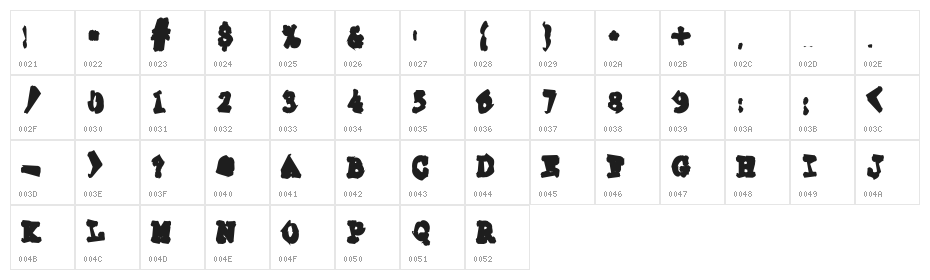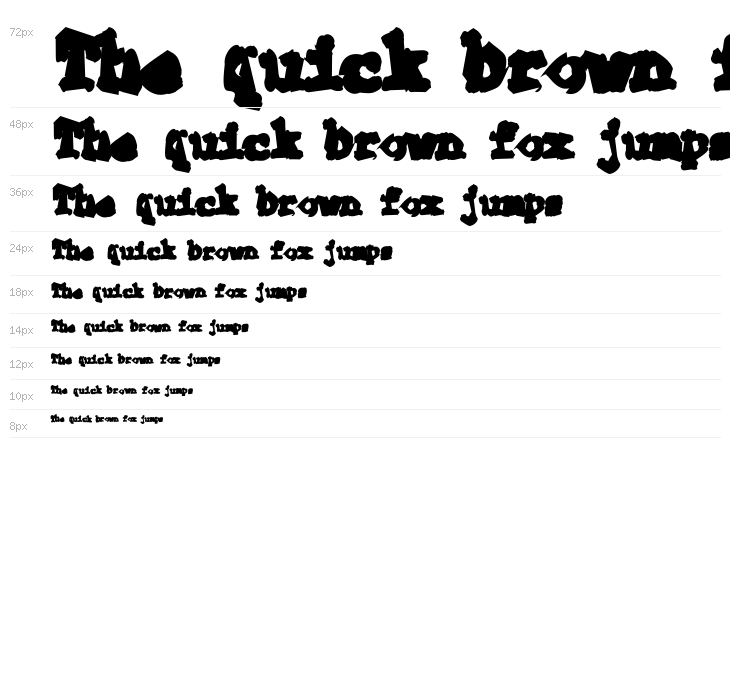
Type2 Font
✎ Decorative
TYPE2 Groß
TYPE2 Kleinbuchstaben
TYPE2 Anderer Schreiben
| Gesamtstil | Artistic, Playful |
| Vorgeschlagene Projekte | Ideal for creative projects such as posters, album covers, and artistic branding that require a bold, unconventional look. |